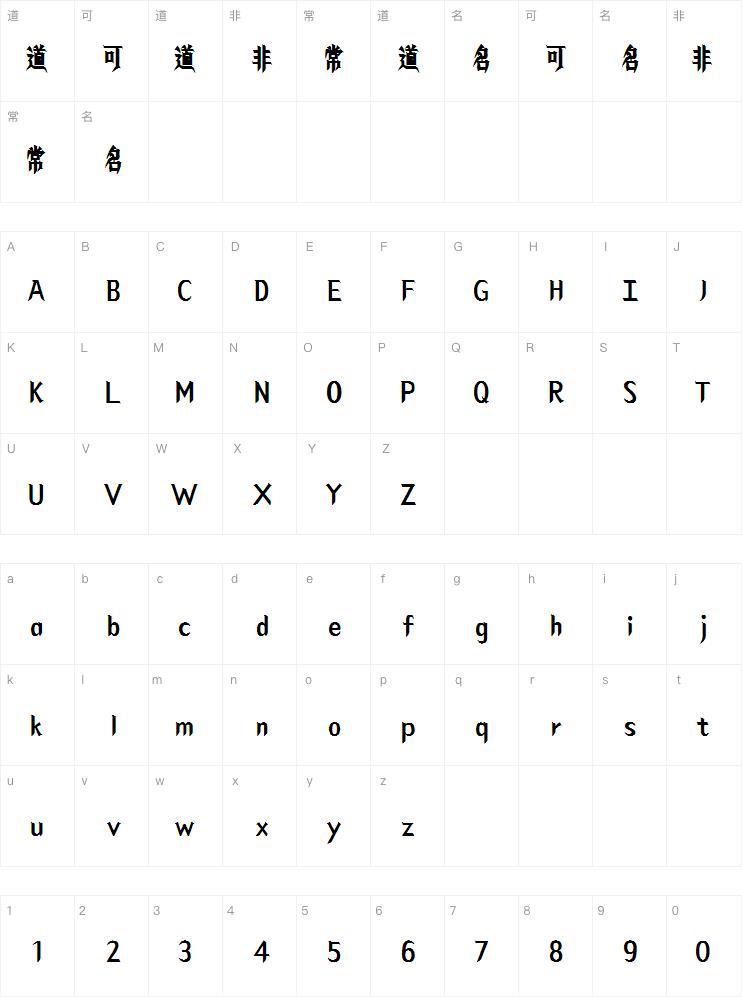
山海格桑卓玛,是一款全新的字体,包含汉字9169个,符号200+个。该字体是一款藏意汉字字体,是一款具有强劲视觉冲击力的装饰性字体。该字体在传统汉字的基础上融合了藏文元素,字体独特,新颖华丽。汉字艺术与藏文元素的融合,藏意十足;个性鲜明的字体特征,散发着藏传佛家气息。在佛教禅意而不失婉约中,感受藏风的魅力;字形比例按照宽高8:10的比例设计,使得字体显高;同时笔画带有尖角装饰,使得字形带有律动感,带来强有力的视觉冲击效果。该字体在传统基础上加入诸多藏文元素,在体现藏文风格的同时呼应了中文的笔画特征,尽量做到易辩、易读,保证了字体的实用性。汉字艺术与藏文文字的融合使得该字体既有着流动的藏意美感,又有着端肃的凝重,在正式用字场合落落大方,在日常使用环境中不失亲切友好,能够更能适应当下时尚潮流的需要,助力各大新产品夺取标题主战场。